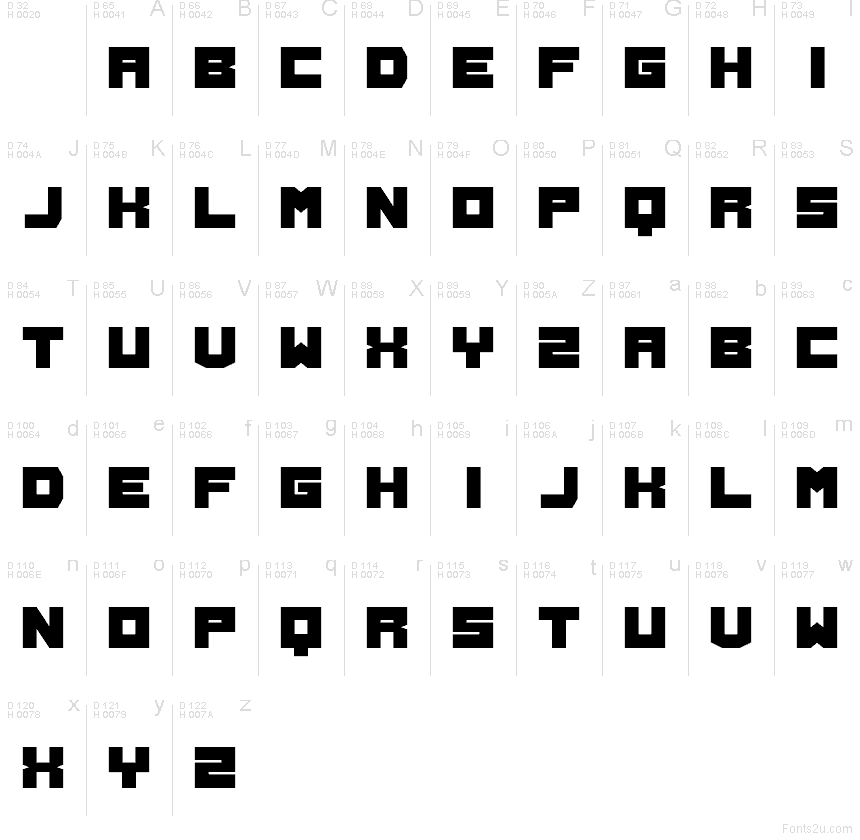
Frula Elegant od Vladimira Nikolice je bezplatný techno font typu display s výrazným retro-futuristickým nádechem. Velká písmena působí, jako by byla vyseknutá z pevných bloků – hranaté tvary, úzké rozestupy a ostré zářezy dodávají písmu strojově přesný rytmus, který se vymyká běžné geometrické jemnosti.
Přirozeně zapadne do sci-fi plakátů, obalů elektronické hudby, herních titulů, grafiky pro technologické akce i kompaktních log, kde tento font zdarma dodá chladný, graficky čistý nádech. Využijete ho pro krátké nadpisy, titulní karty nebo monogramy, u nichž chcete, aby písmena působila jako modulární dílky přesně zapadající do sebe.